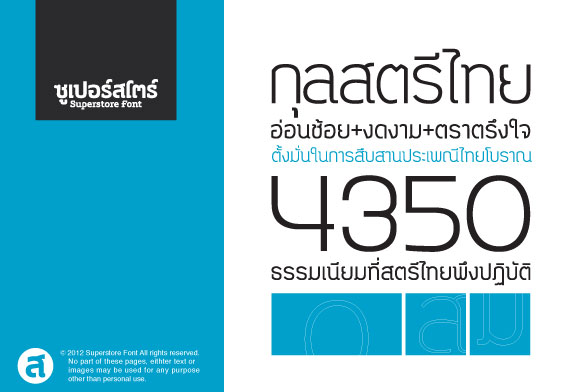
Kunlasatri/กุลสตรี
(light/regular/bold)
“กุลสตรี” คืออีกหนึ่งฟอนต์ซึ่งจัดเป็นฟอนต์ที่สร้างขึ้นมาเพื่อศึกษาวิธีการทําตัวอักษรที่ถูกต้อง ดังนั้นจึงมีคุณภาพที่ลดหลั่นจากฟอนต์ในชุดใหม่ของซูเปอร์สโตร โดยเราเปิดให้ทุกท่านสามารถเข้าไป download ใช้ได้ฟรีโดยถูกต้องตามลิขสิทธ์